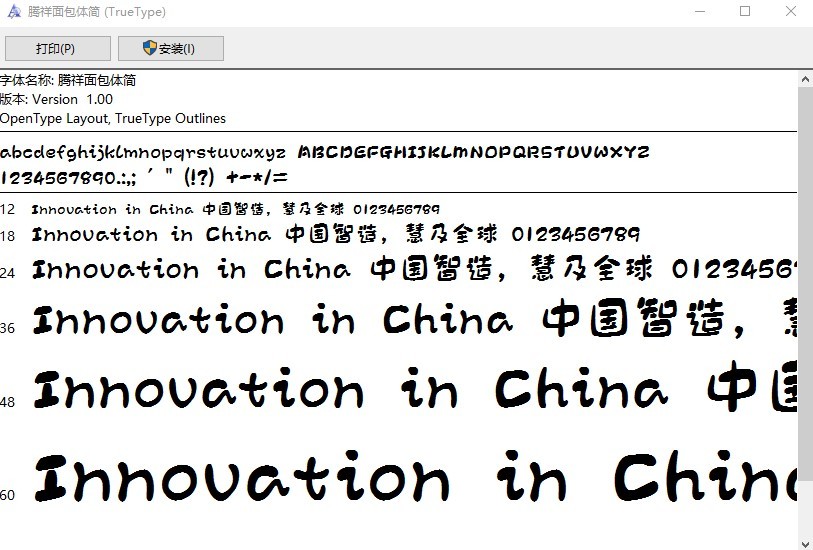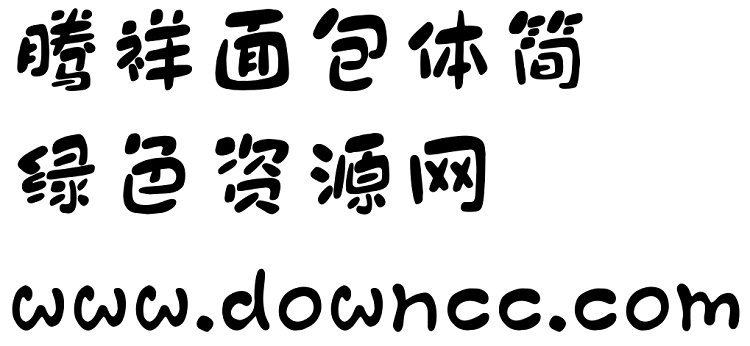
騰祥面包體簡(jiǎn)體是一款騰祥字庫(kù)旗下的中文簡(jiǎn)體字體,筆畫(huà)圓潤(rùn),風(fēng)格鮮明,簡(jiǎn)單又可愛(ài),極具藝術(shù)設(shè)計(jì)性,充滿(mǎn)童真色彩??梢赃m用于平面設(shè)計(jì)、包裝設(shè)計(jì)、海報(bào)設(shè)計(jì)等兒童出版領(lǐng)域,支持多個(gè)操作系統(tǒng),使用起來(lái)十分簡(jiǎn)單。
騰祥字庫(kù)(tensentype)由北京騰祥科技開(kāi)發(fā)有限公司和北京騰祥世紀(jì)軟件銷(xiāo)售有限公司組成(同時(shí)簡(jiǎn)稱(chēng)“騰祥公司”)。北京騰祥科技開(kāi)發(fā)有限公司為字庫(kù)研發(fā)團(tuán)隊(duì),北京騰祥世紀(jì)軟件銷(xiāo)售有限公司為騰祥字庫(kù)市場(chǎng)團(tuán)隊(duì)。
在2012年以前,騰祥公司致力于為國(guó)內(nèi)外客戶(hù)加工字庫(kù),曾為臺(tái)灣、日本、德國(guó)、國(guó)內(nèi)客戶(hù)成功開(kāi)發(fā)過(guò)臺(tái)灣繁體字庫(kù)、日本漢字庫(kù)、國(guó)標(biāo)gb18030字庫(kù)等等。
作為一家專(zhuān)業(yè)的、知名的字體公司,騰字庫(kù)產(chǎn)品發(fā)展到百余款。其中具有代表意義的如:騰祥嘉麗圓體系列(gb18030)、睿黑智黑系列、金磚黑、沁圓、凌黑、麥黑、潮黑、潮圓、魅黑等。